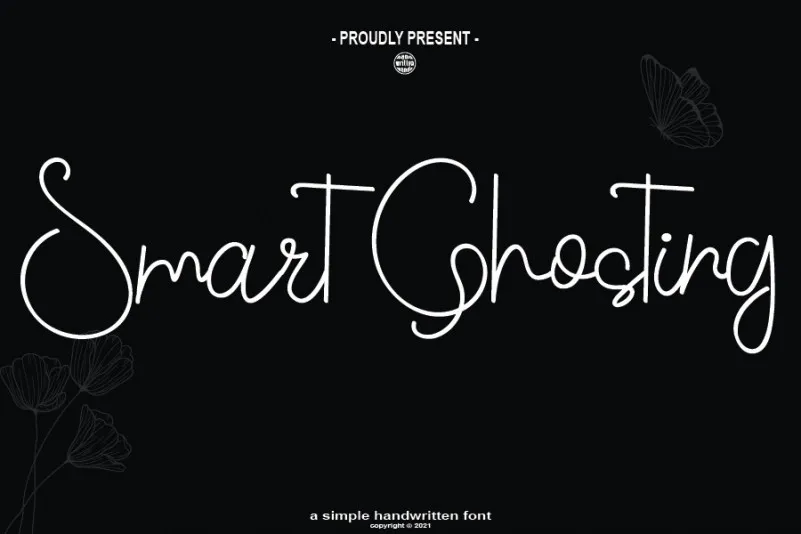
Smart Ghosting Font – Download Grátis
Esta é uma fonte autografada que abrange todas as áreas com facilidade e flexibilidade. Ela tem um toque suave, sendo ao mesmo tempo quirkie e alegre. Esta font irá transformar cada ideia para seu projeto em obras de arte reais. Divirta-se com essa linda fonte e explora suas infinitas variações. A fonte ‘Smart Ghosting Font’ é perfeita para designers, artistas ou qualquer pessoa que procura um tom autêntico e divertido na sua próxima criação visual. Com a elegância natural da escrita semelhante a uma mão, essa fonte será o elemento de destaque em seu próximo projeto.